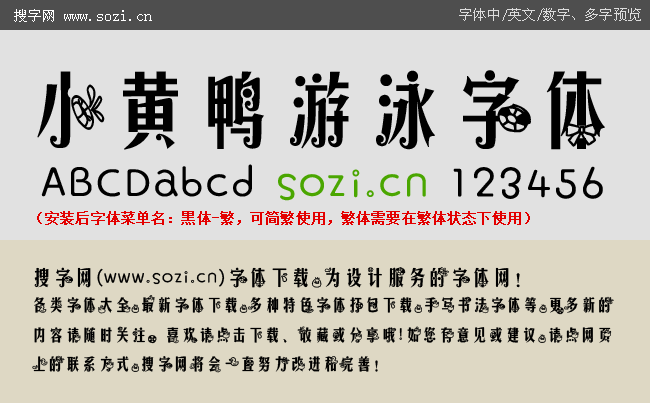
小黄鸭游泳字体
搜字网给大家提供一款小黄鸭游泳字体手机中文字体下载。这款手机字体是在长艺体笔画间插入了一些卡通图案。长艺体笔画既有黑体的粗壮醒目,又有宋体的秀美柔和,加上艺术性的圆球形点、起笔如蝌蚪形的顿点、螺蛳转似的小钩,配以修长的字形,美观而不落俗套。加入了卡通图案后又增添了趣味性,特别适合喜欢手机字体个性一些的朋友在手机上安装使用。